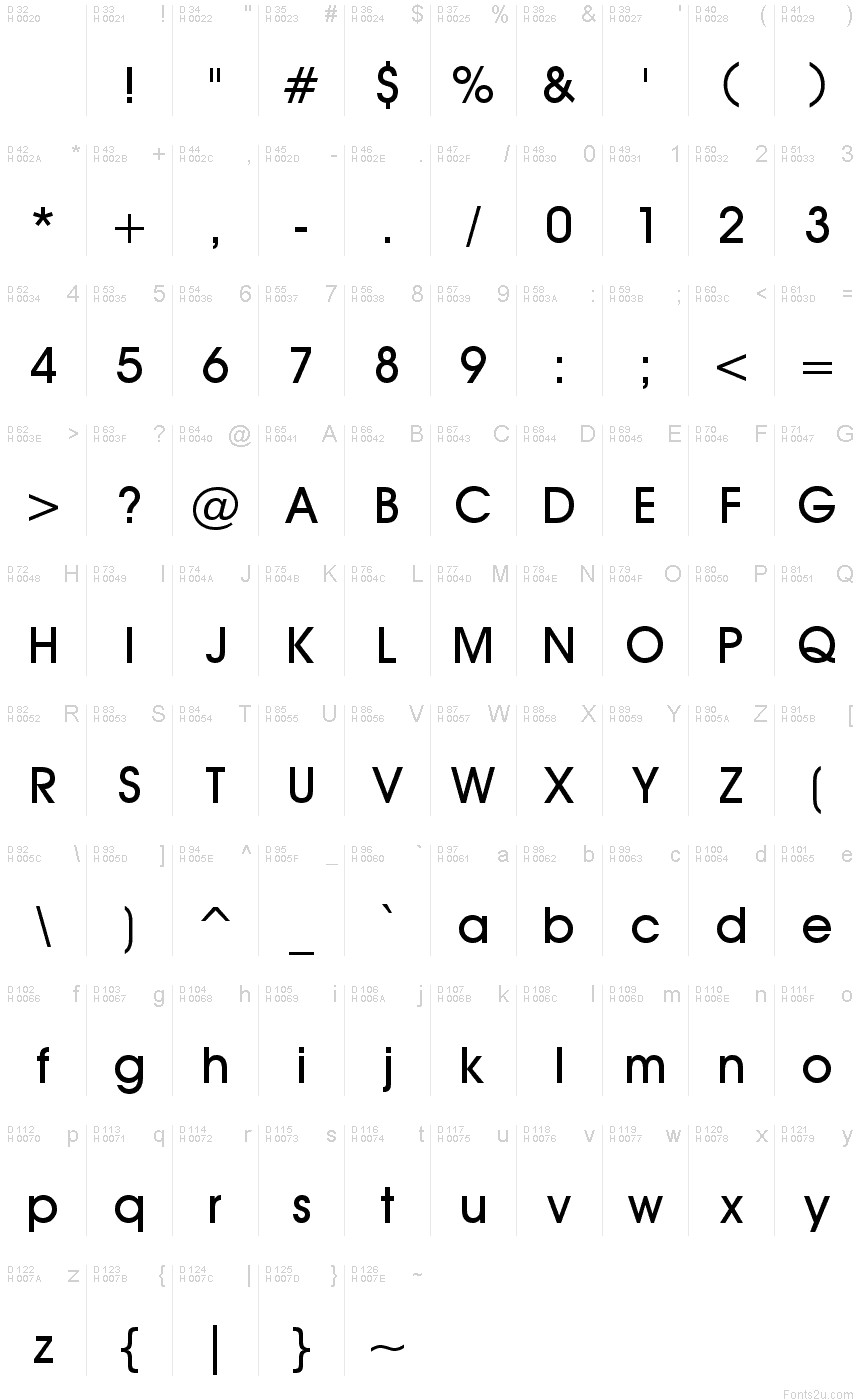
Decker Bold je bezplatné geometrické bezpatkové písmo složené z širokých kruhových tvarů, nízkého kontrastu tahů a pevné siluety s nápadně otevřenými, čistými křivkami. Písmo působí ostře, robustně a výrazně strojově.
Technologická značka představuje obzvláště přesvědčivou volbu, protože tato pevná geometrie se může uplatnit napříč logy, obaly produktů a grafickým rozhraním, aniž by ztratila svůj přímý charakter. Hodí se také pro spotřební elektroniku a software vytvořený pro současné, designově uvědomělé publikum, které reaguje na jednoduché tvary a technicky propracovaný vzhled.
Decker Bold